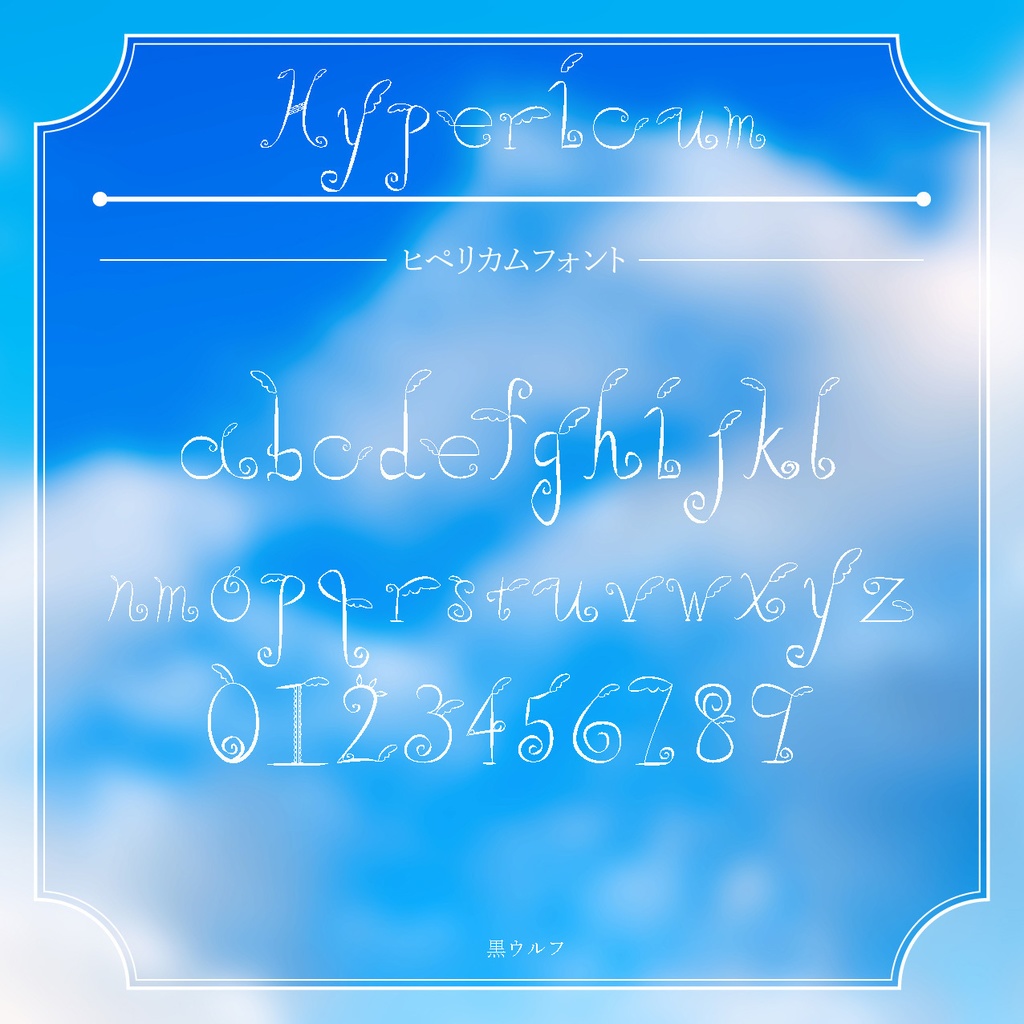
【無料版あり】ヒペリカム天使フォント
自作小説『ヒペリカム』に登場する天使達が使っていそうな文字をフォントにしました。 装飾に羽根や蔦をイメージしたモチーフをつけています。 ファンタジーな世界観の作品等ですと、雰囲気あるのかなと思います。 装飾が多いので、他の欧文フォントと組み合わせて使用することで視認性をよくすることもできるかと。 フォント情報 欧文フォント 大文字+小文字+数字が収録されています。 無料版は大文字のみです。 利用規約(2023.12.12現在) 詳しくは素材集内の利用規約または無料ダウンロードの利用規約をご覧ください。 この素材(画像素材、フォント等を含む)を利用する場合、利用規約に同意した前提となります。 こちらの都合により利用規約の変更をした場合、利用規約はウェブショップ「おおかみしょうてん」の商品ページから再度確認をお願いします。 この素材は商用利用可です。 使用OK ・イラスト、漫画、小説等の印刷物での使用 ・商標登録や意匠登録をしないデザインへの使用 ・ホームページやブログでの使用 ・動画への使用 ・ゲームコンテンツへの使用 ・TRPG(ココフォリア等のシステム)での使用 ・同人誌や同人グッズへの使用 が挙げられます。 また、使用範囲に関しては今後更新される事もありますので、使用する場合は改めて利用規約をご確認ください。 また素材は加工が可能となっています。 色の変更や縦横比の変更等、ご自由に加工していただいて構いませんがデザイン性が保持されるかどうかは保証できません。 NG ・自作発言 ・素材の再配布、貸与、譲渡、転売 ・購入者以外の第三者による使用 ・インターネットやCD/DVDなどを介して複数の利用者間での素材のシェア、共有 ・商標登録、意匠登録 ・素材のみを変形、加工した物の頒布 ・犯罪、反社会的な行為、その他法律に反する物への使用 ・政治、宗教活動に関する使用 ・サムネイルに使用している見本の使用 ・素材を使用したキャラクターの作成(※1) ・公序良俗に反する作品への使用(※2) ・その他、私(黒ウルフ)が不適切と認めた使用 利用する上で購入してダウンロードしていただければ問題なく使用できるかと思われます。 使用許可は必要ありません。 またこの素材は素人制作ですので技術力やクオリティーに関するご意見や苦情は一切受け付けません。 その点をご理解の上で使用してください。 また、ダウンロードした素材の著作権は私(黒ウルフ)にあります。 著作権表記(クレジット表記やリンクの表記等)については任意ですがしていただけると嬉しいです。 規約に違反した場合、損害賠償を求める事もあります。 この素材を使用した上でトラブルが発生しても私(黒ウルフ)は一切の責任を負いません。 素材のダウンロードの中止、変更、終了等があった場合は素材に関しての著作権は私にありますが、そのまま継続して使用が可能です。 また、中止や変更、終了等があった場合に通知をすること無く停止する場合があります。 その際に起きるトラブルについても一切の責任を負いません。 最後にこの素材に関する苦情やそれに対する対応、返金対応等は一切受け付けませんので、よろしくお願いいたします。